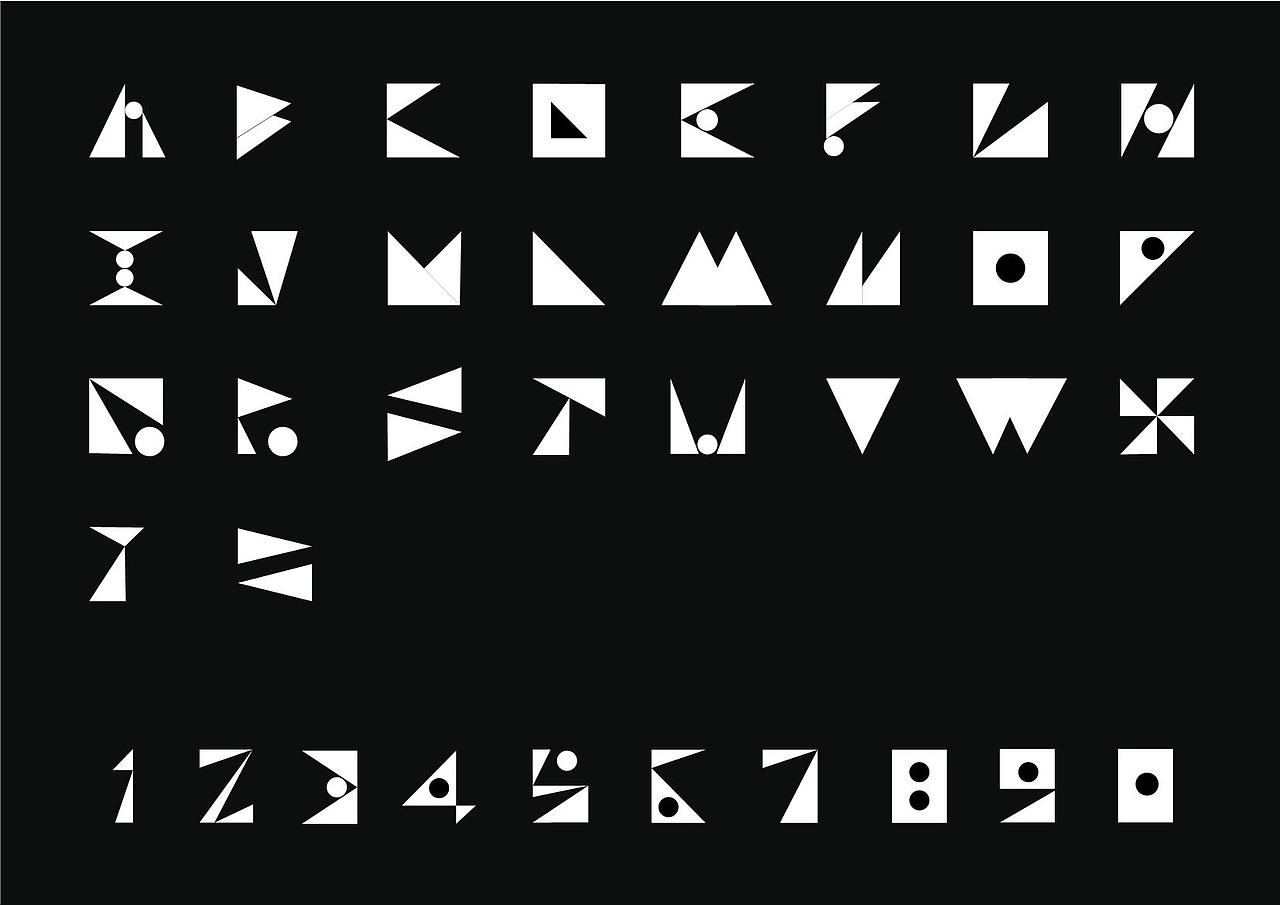
字体设计 - Triangle, Circle and Rectangle
Modular Typeface 的设计,三个元素贯穿整个设计,由格子纸起草确保每个字母大小相等。
设计灵感来自Bauhaus style,本设计主要聚焦在三角形,矩形与圆形的相互搭配与融合,体现一种尖锐却摩登的设计风格。
Final design
Draft.